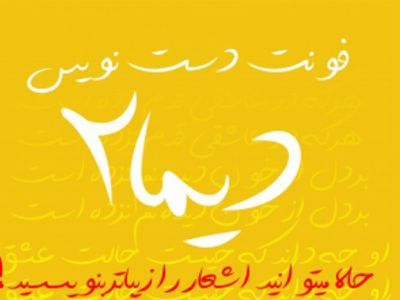
فونت زیبای دیما مهدی — نمونه متن فارسی ۱۲۳۴۵۶۷۸۹۰
این قلم رو خیلی وقت پیش کار کردم ، اما فرصت انتشارش نرسید و نتوانستم منتشر کنم. این فونت فکر کنم هم برای کارهای خاص و هم برای وب فونت خوبی باشه
قلم زیبای دیما مهدی منتشر شده است.
- دیما مهدی